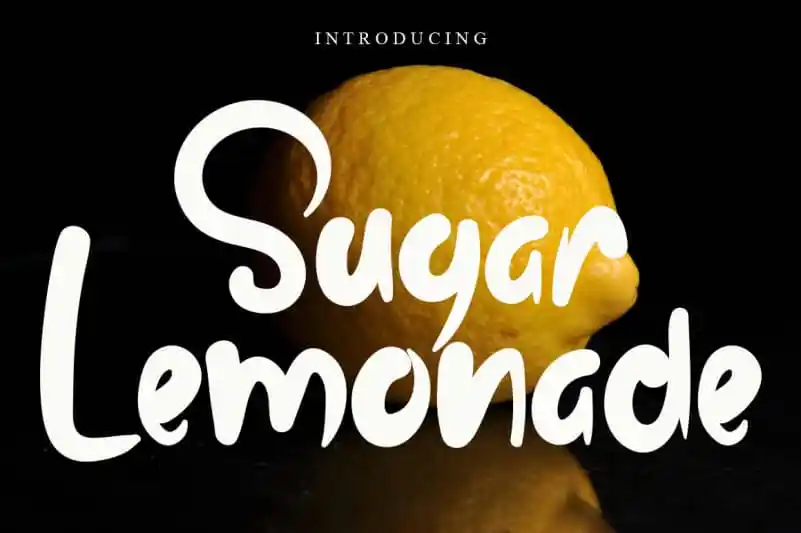
Sugar Lemonade Script Font – Download Grátis
Sugar Lemonade Script Font é uma fonte script desenhada com uma paleta leve e amigável, inspirada na pintura branca que transforma letras em texturas lúdicas e um pouco estranhas. Esta fonte traz à vida cada projeto com sua personalidade encantadora e alegre, tornando-a perfeita para designers gráficos de todo o Brasil. Sua simplicidade criativa é ideal para criar layouts modernos e atemporais, destacando-se nas mais diversas aplicações digitais e impressivas. Com Sugar Lemonade Script Font, você pode adicionar um toque único aos seus projetos, sabendo que receberá resultados surpreendentemente agradáveis.